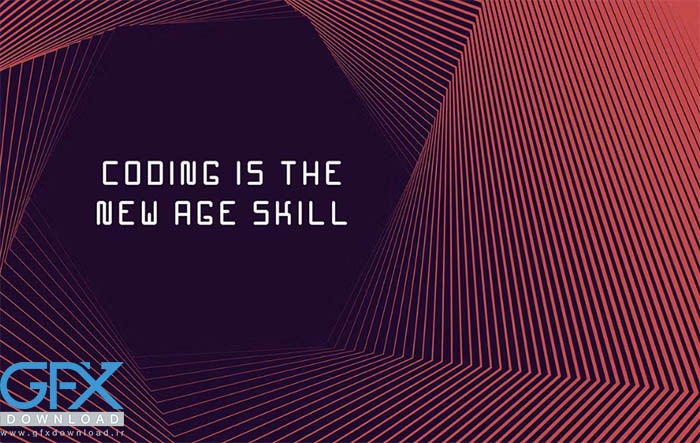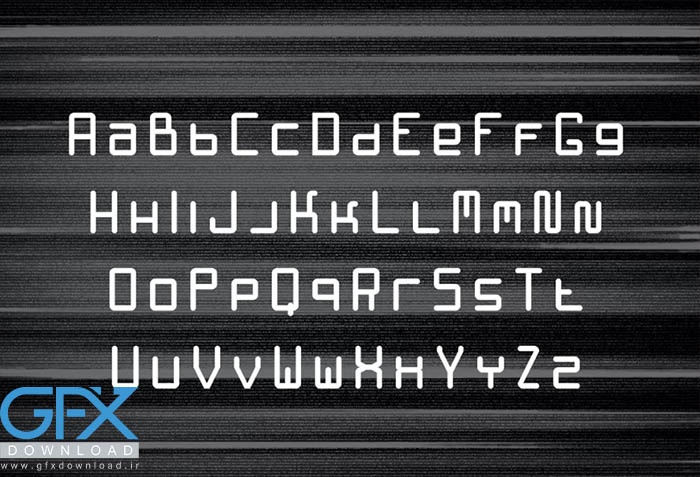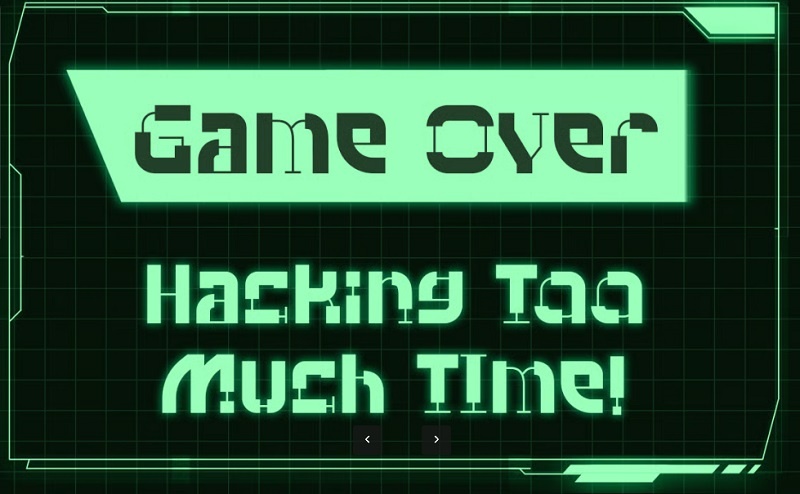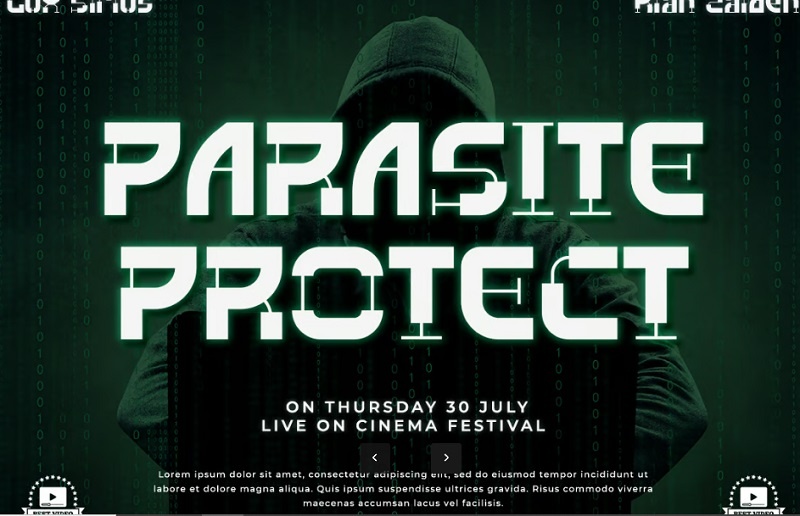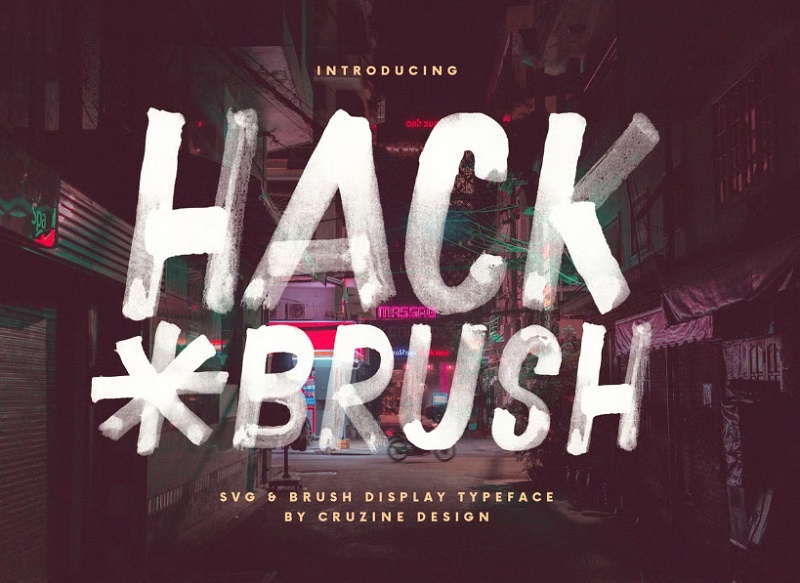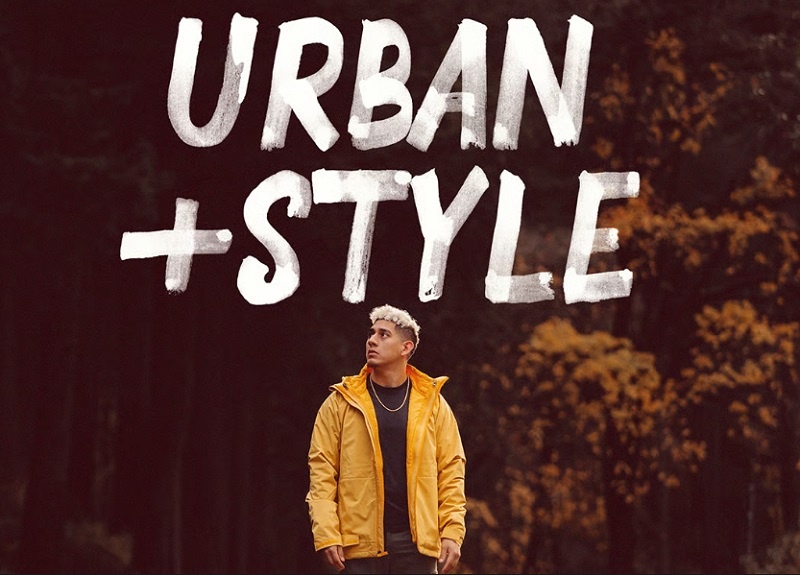
هکر یک فونت نمایش گرد است. این فونت ممکن است شما را به یاد دهه 1980 بیاندازد، زمانی که انقلاب کامپیوتری مرز جدیدی را باز کرد. فونت هکر و فناوری Hacker را می توان برای هر چیزی که مربوط به سایبر، امنیت، اینترنت، فناوری، ارتباطات، کدگذاری، داده ها، الکترونیک، ریاضیات، شبکه، تجارت، ارتباطات و موارد دیگر باشد استفاده کرد.
دانلود فونت تکنولوژی با استایل فناوری اطلاعات و هکری
اگر به دنبال یک فونت تکنولوژی مدرن و متفاوت هستید که حال و هوای دنیای دیجیتال و آینده نگر را منتقل کند، فونت های حوزه فناوری اطلاعات انتخابی ایده آل هستند. این سبک فونت ها معمولاً با الهام از رابط های کاربری، کدنویسی و فضای سایبری طراحی می شوند و برای پروژه های مرتبط با امنیت، برنامه نویسی و تکنولوژی بسیار کاربردی اند. استفاده از فونت فناوری اطلاعات در طراحی وب سایت، پوستر، رابط کاربری یا محتوای گرافیکی باعث می شود پیام شما حرفه ای تر و تخصصی تر دیده شود. همچنین اگر به دنبال دانلود فونت هکر فناوری اطلاعات هستید، این فونت ها با ظاهر دیجیتال، خطوط شکسته و حس رمز آلود، گزینه ای عالی برای پروژه های مرتبط با هک، امنیت شبکه و فضای سایبری محسوب می شوند.
ویژگی های فونت انگلیسی هکر و فناوری سایت جی اف ایکس دانلود
✅ نام فونت 1: Hacker ✅ نام فونت 2: Hacklife